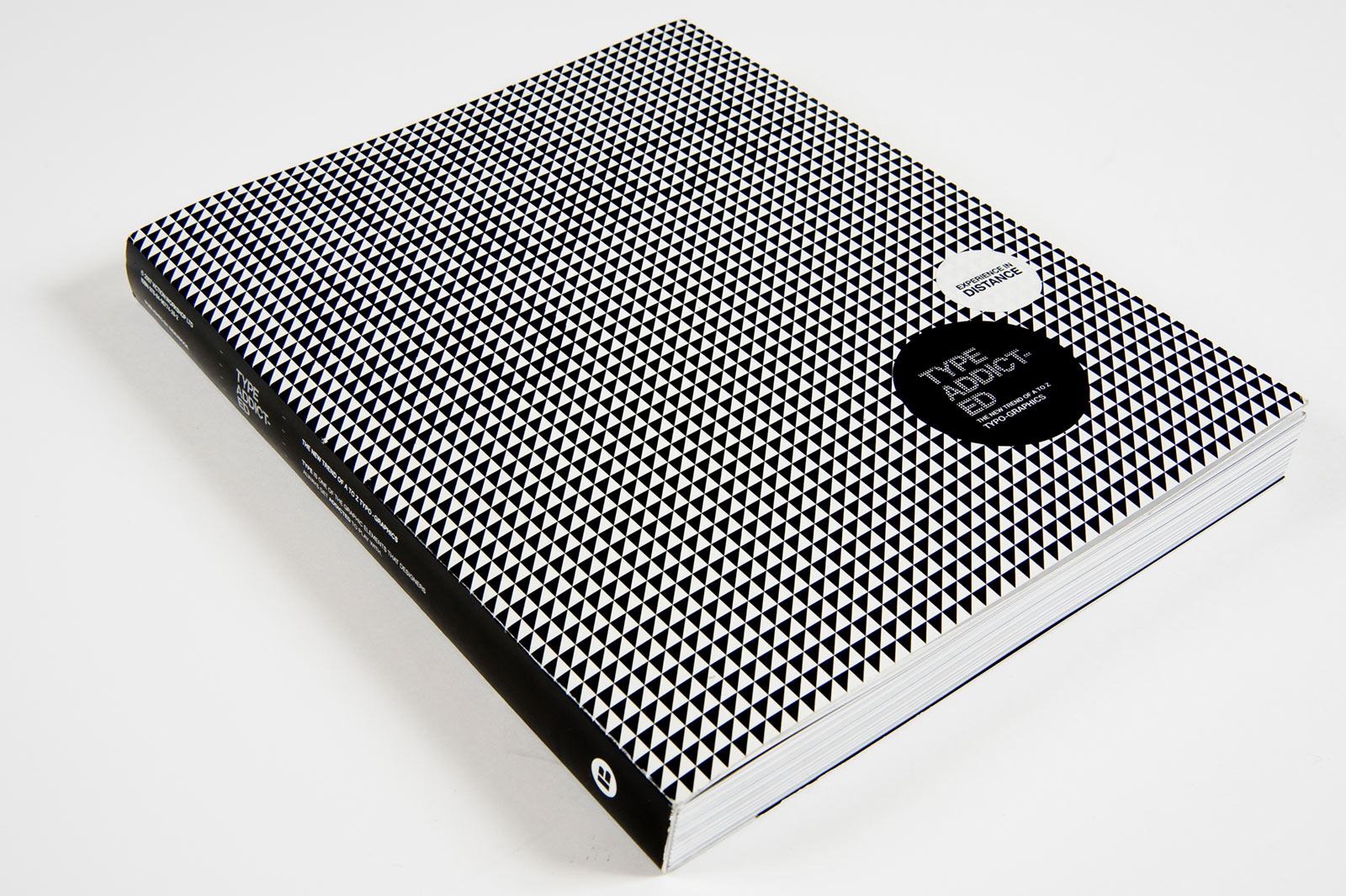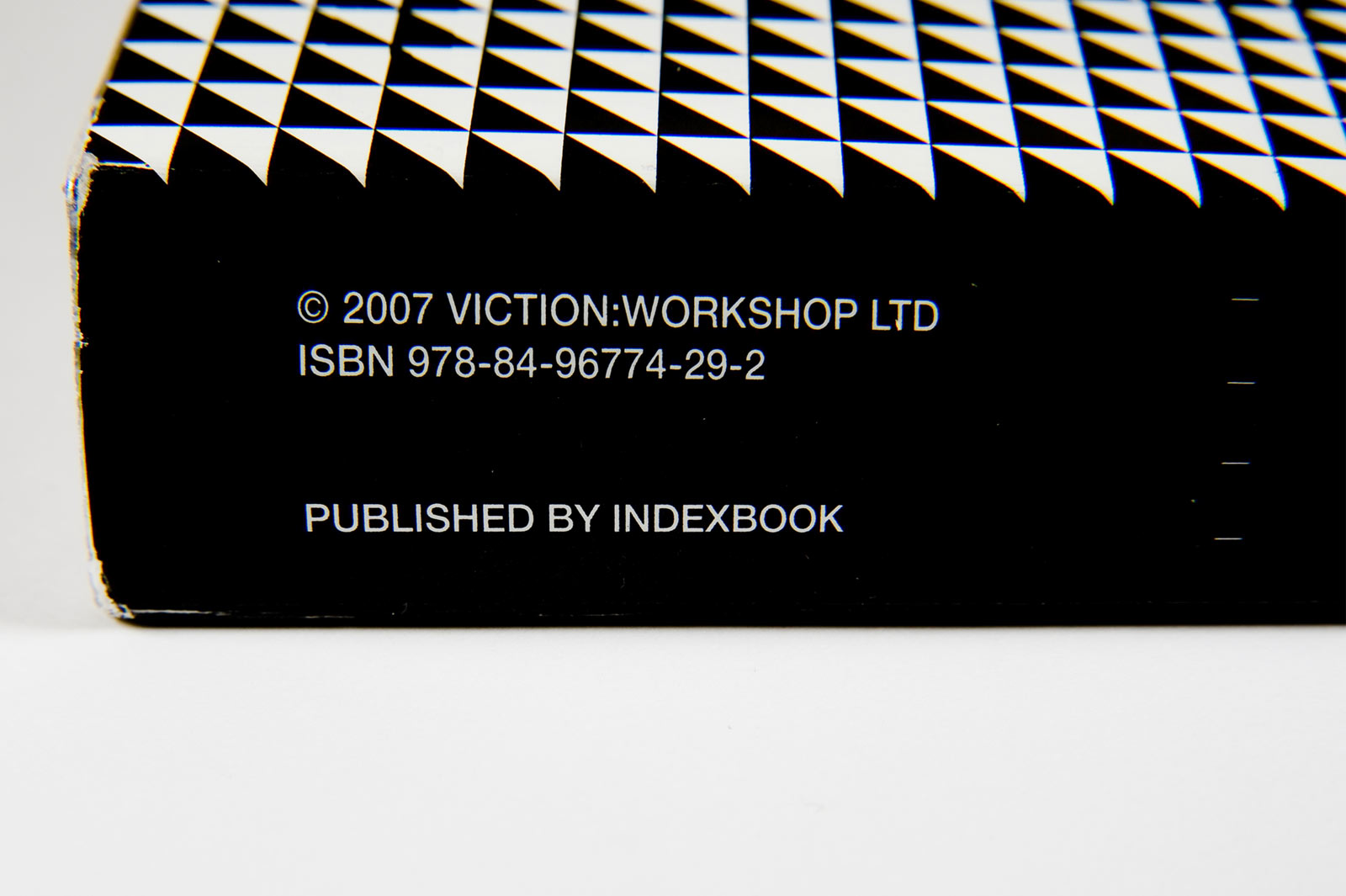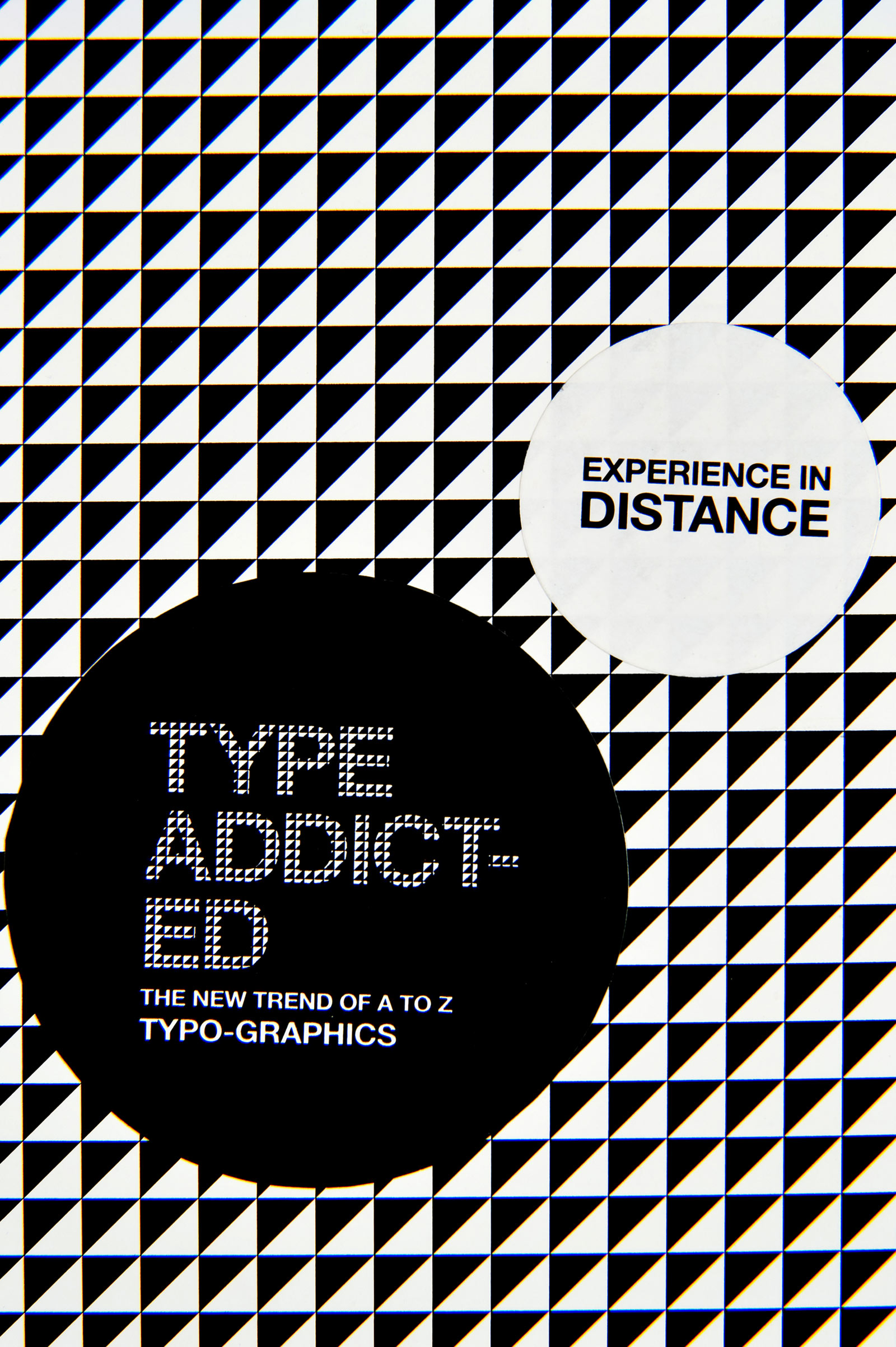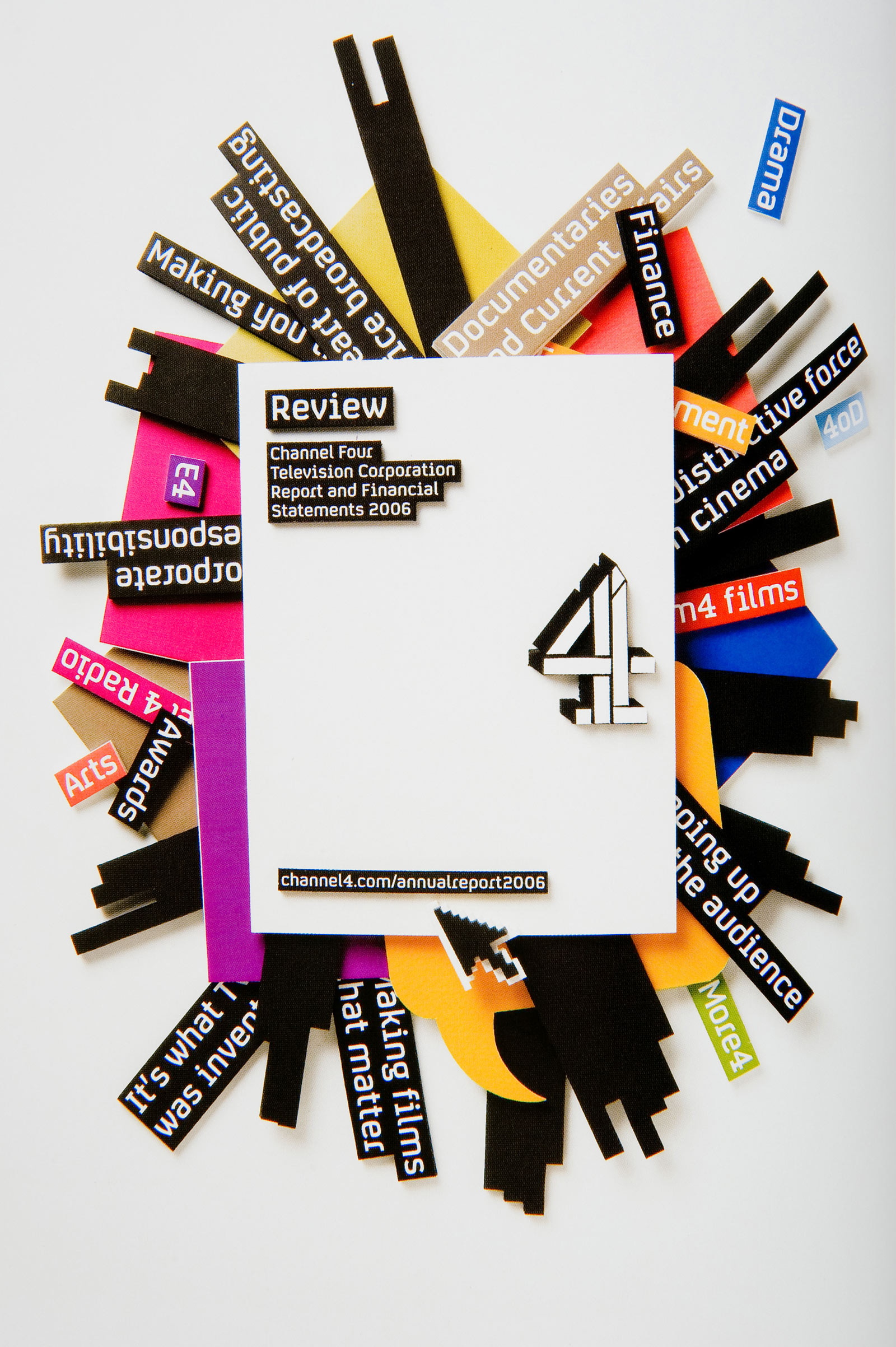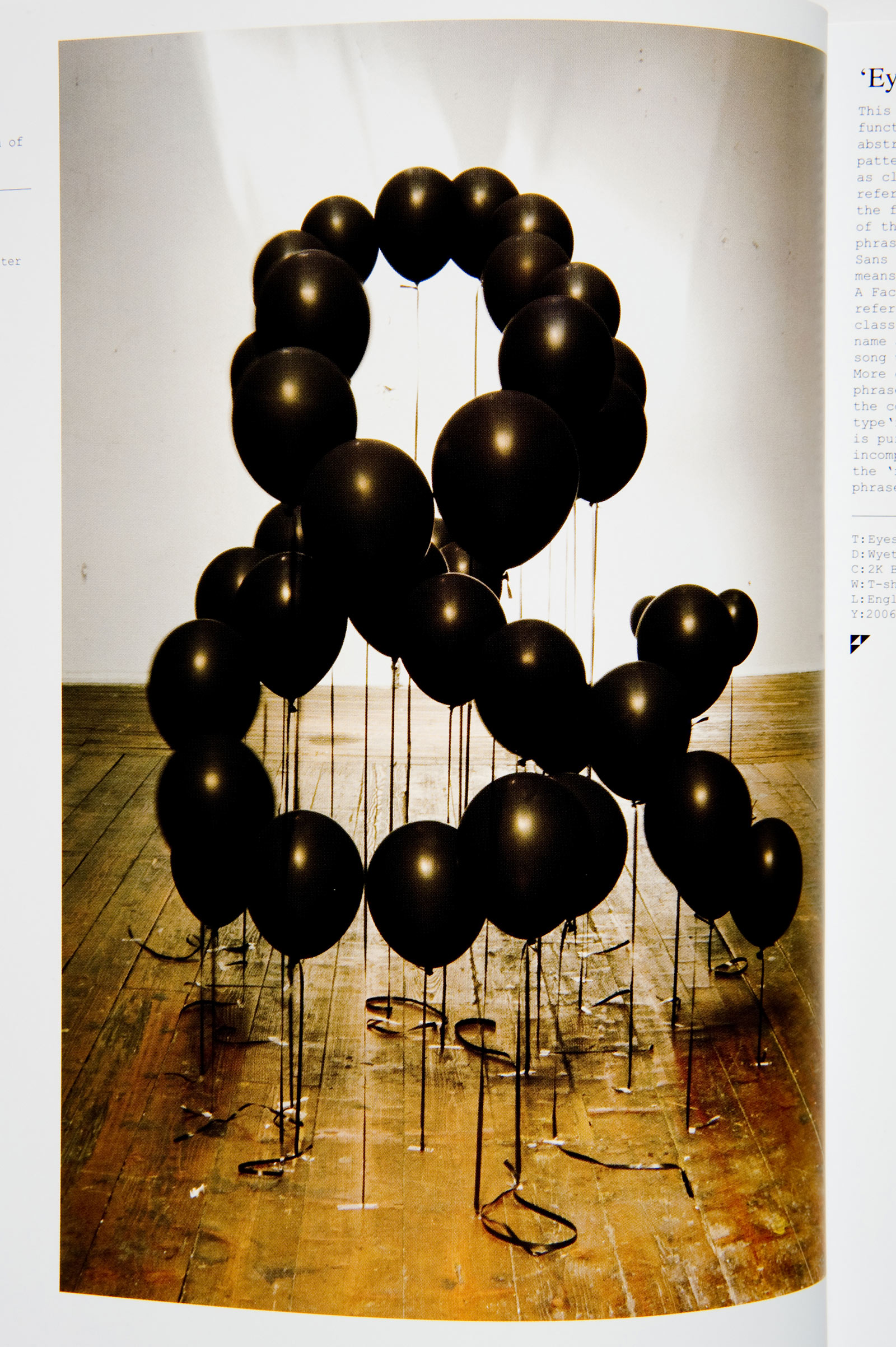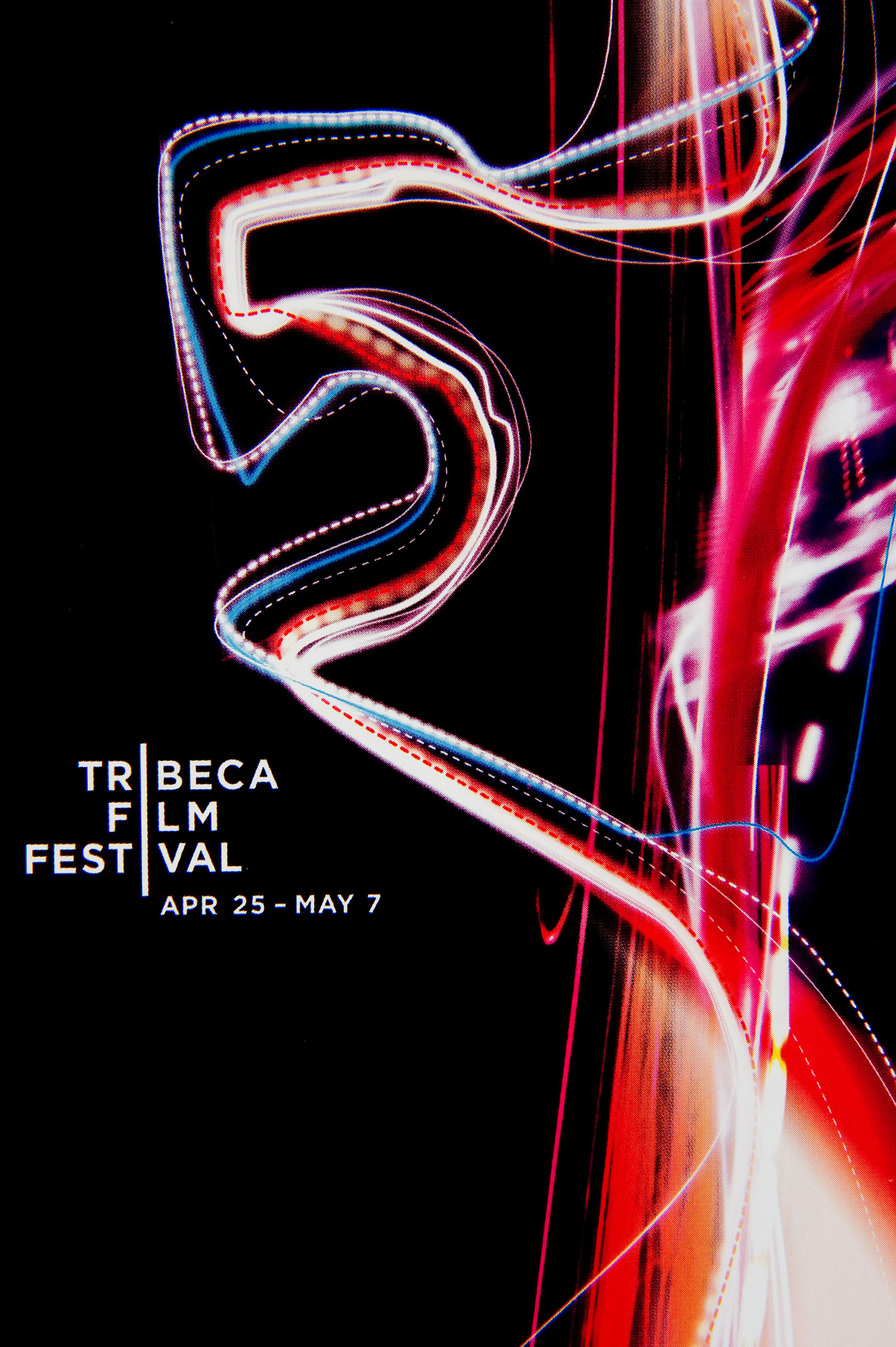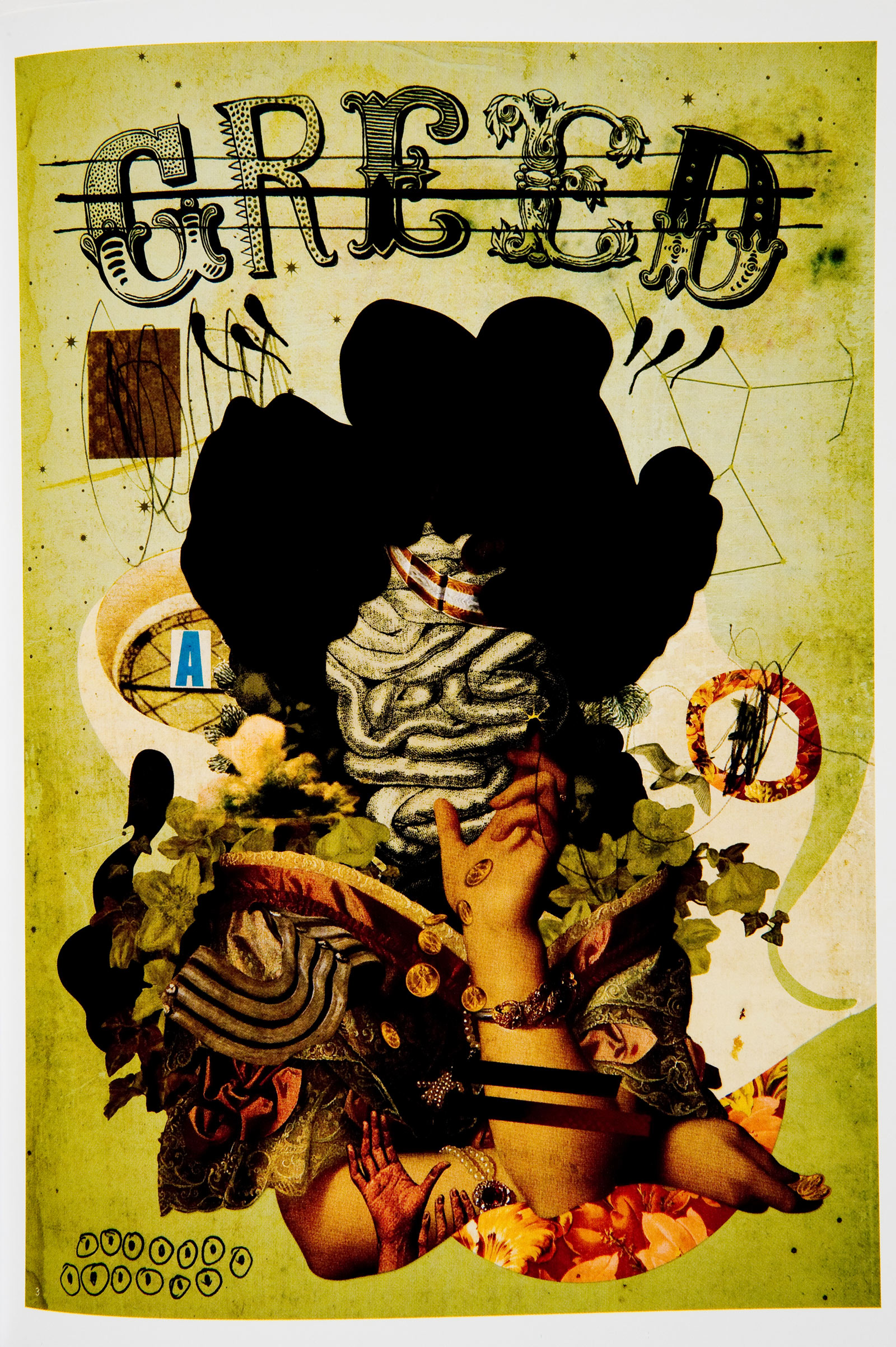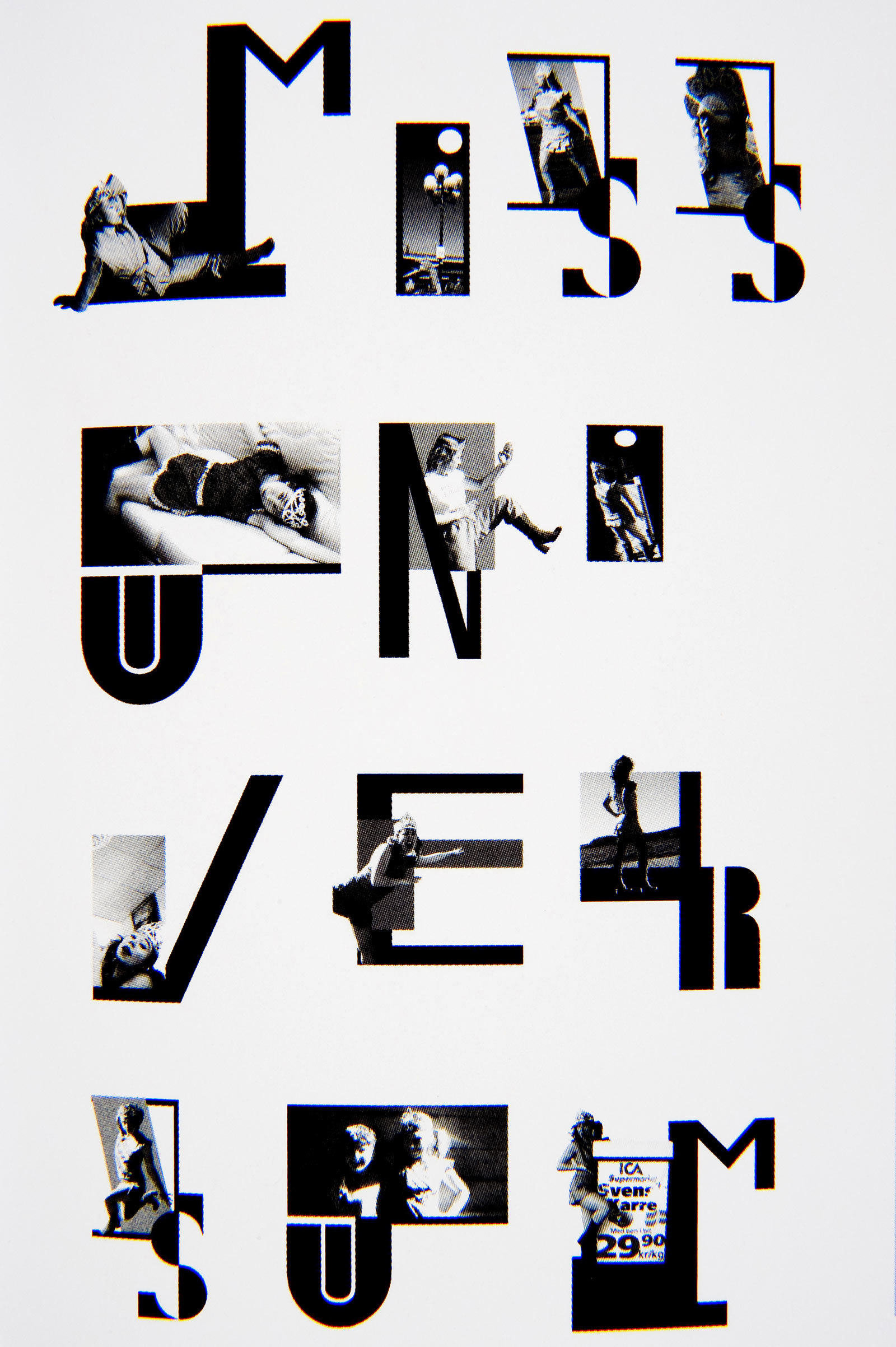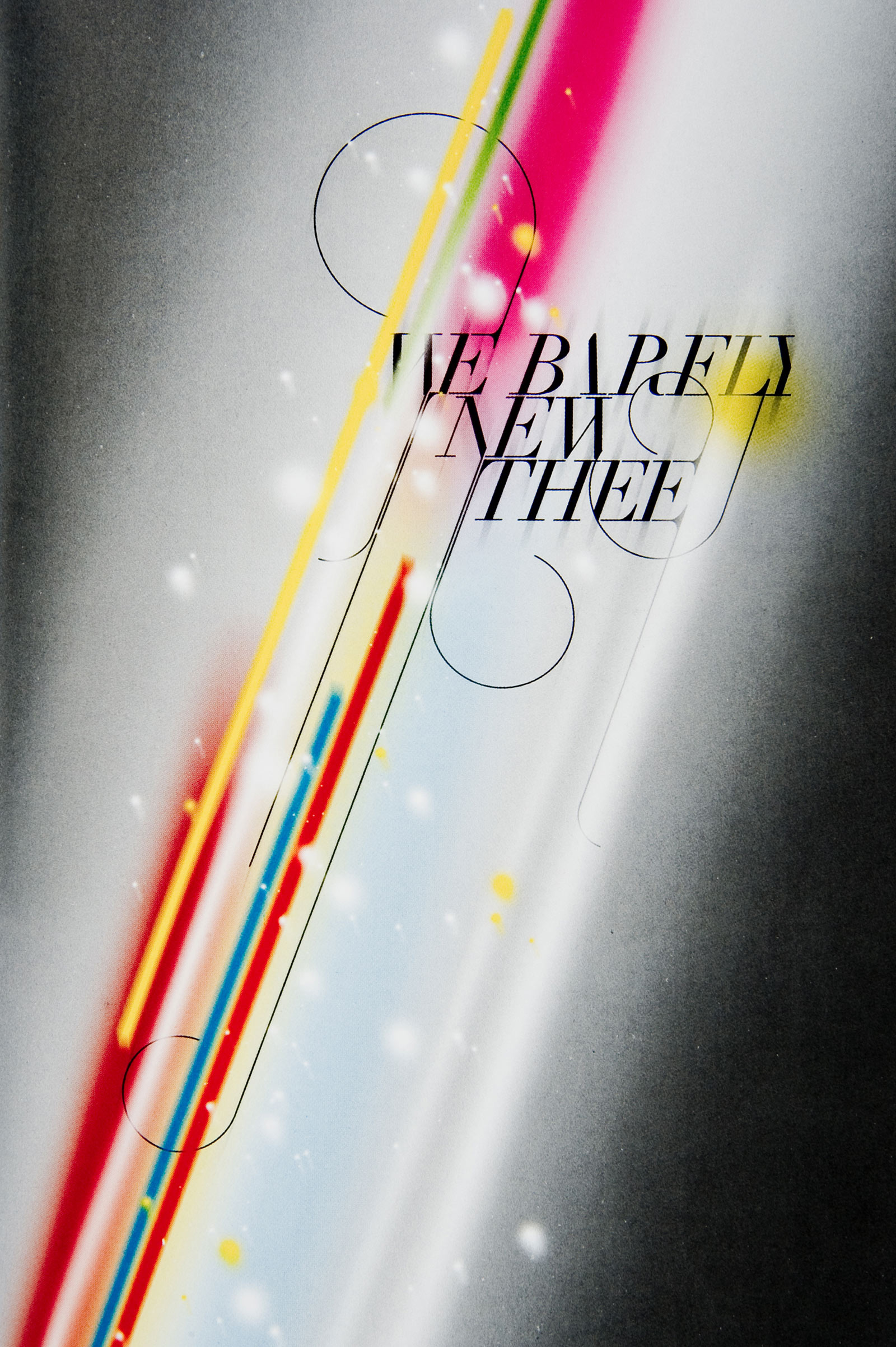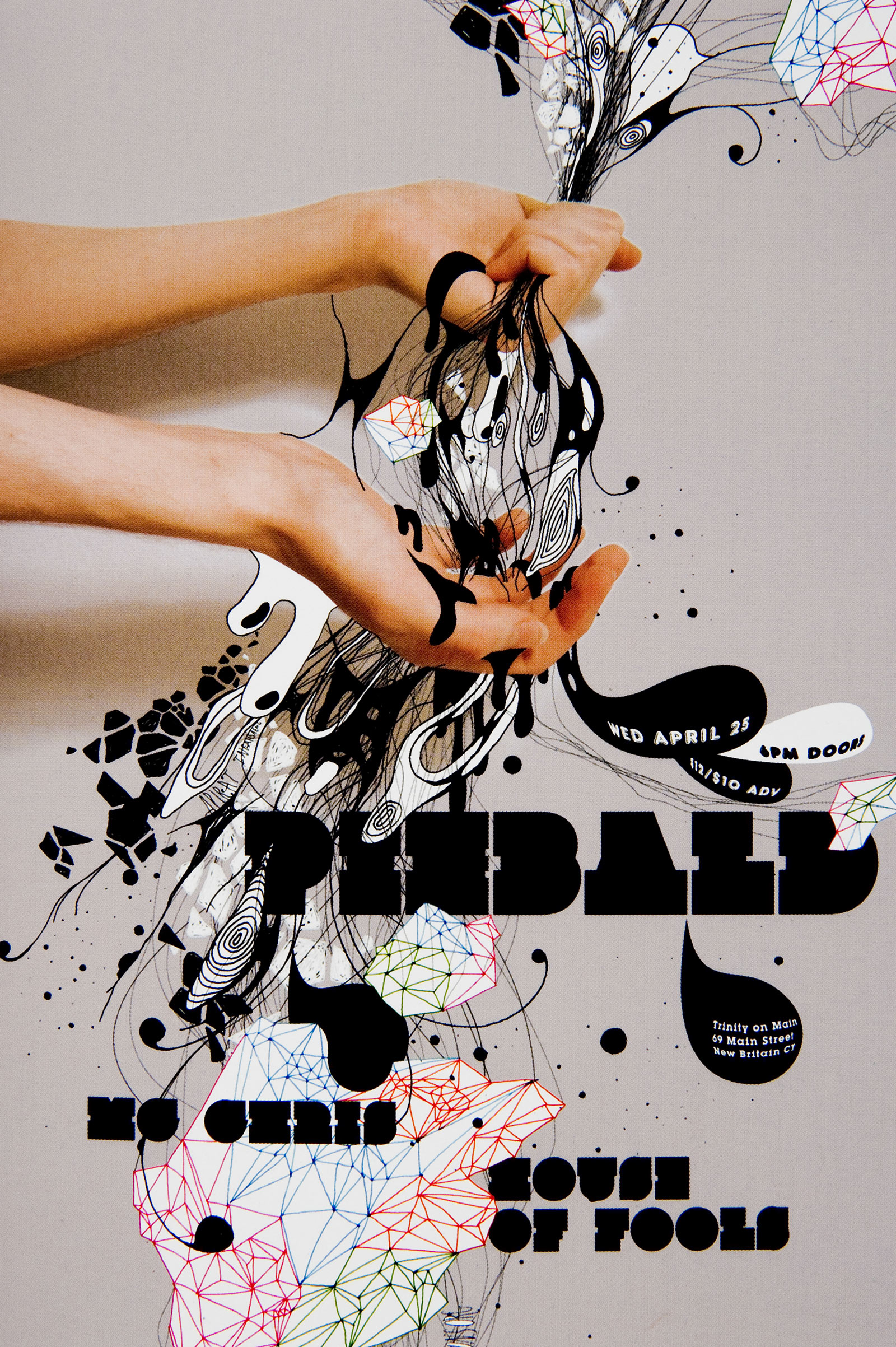
Type Addicted | Un coup de foudre chez Artazart
Oui je sais, je mesure ma chance chaque week-end ensoleillé, lorsque je déambule le long du canal Saint-Martin. Et, sous un soleil de printemps, quand passant devant la vitrine orange fluo d’Artazart je ne peux résister, une fois de plus d’entrer dans l’antre. Serrant désespérément mon portefeuille dans l’espoir de résister à quelques tentations bien onéreuses :-)
Mais là, en feuilletant quelques bouquins, dont celui de Tschichold que je repousse à chaque reprise à la «prochaine fois», je tombe d’un coup sur ce livre Type Addicted, dont voici quelques morceaux choisis. Je vous les laisse découvrir, tant la poésie et la recherche typographique font bon ménage. Je vous laisse savourer l’humour et la sensualité des compositions qui ne disent plus papier ou écran, puisque de toutes façons chaque création passera à un moment ou un autre au tamis du numérique.
Il faut juste oublier les règles, les codes, pour en découvir de nouvelles, propres à chaque créateur. Et c’est là une joie sans borne que de sentir une telle fraîcheur, un tel enthousiasme, un renouveau à chaque page que je tourne pour me rassurer, non la typo n’est pas moribonde, non elle n’est pas «démodée». Elle est typo, c’est à dire signe. Elle fait sens, pas toujours d’ailleurs, et tant pire pour le spectateur et, l’auteur…
Mais lorsque la confusion du sens et de la forme sont au rendez-vous alors, c’est l’explosion et la sérénité. Le monde des signes. Merveilleux et éternel.